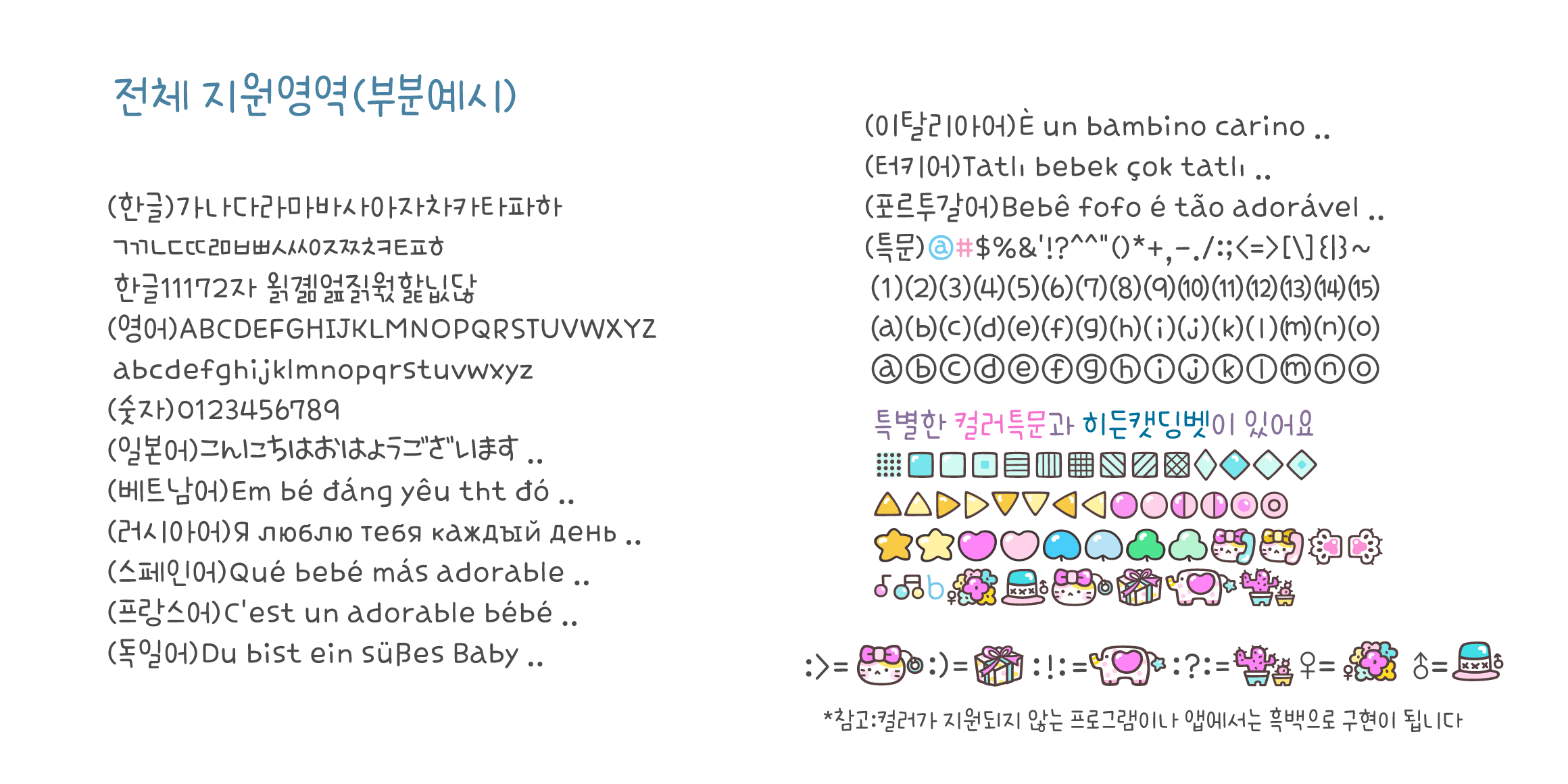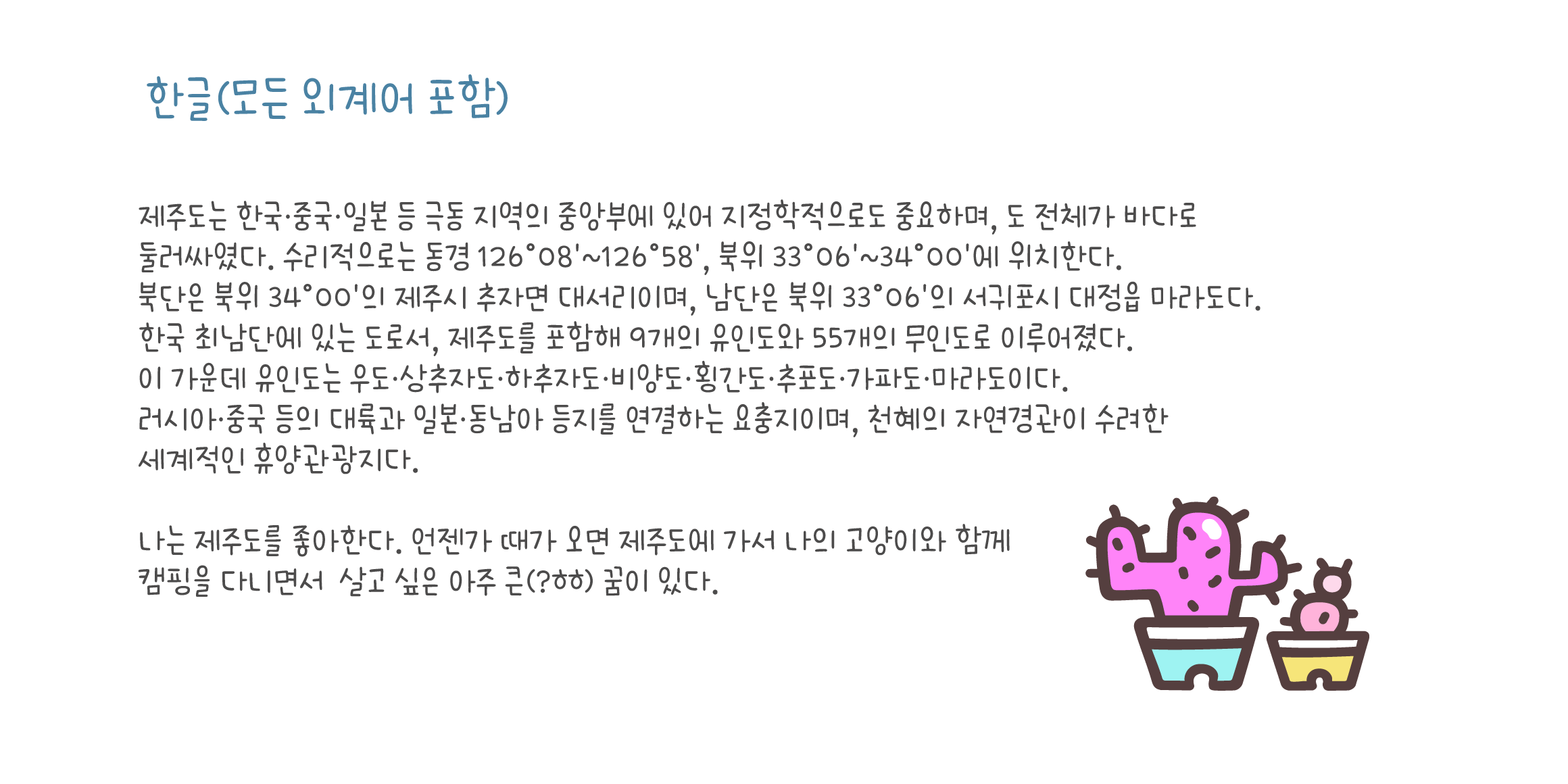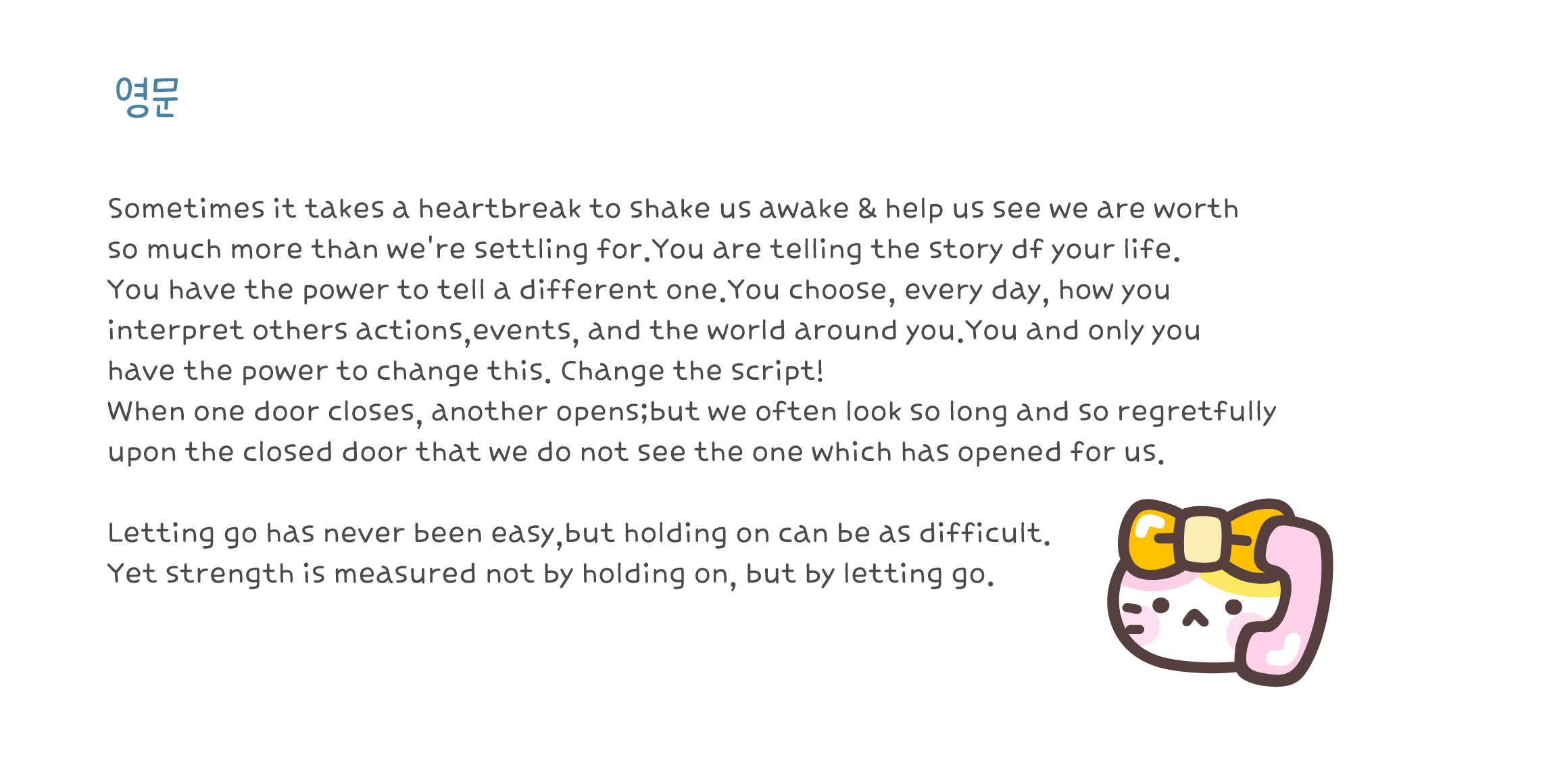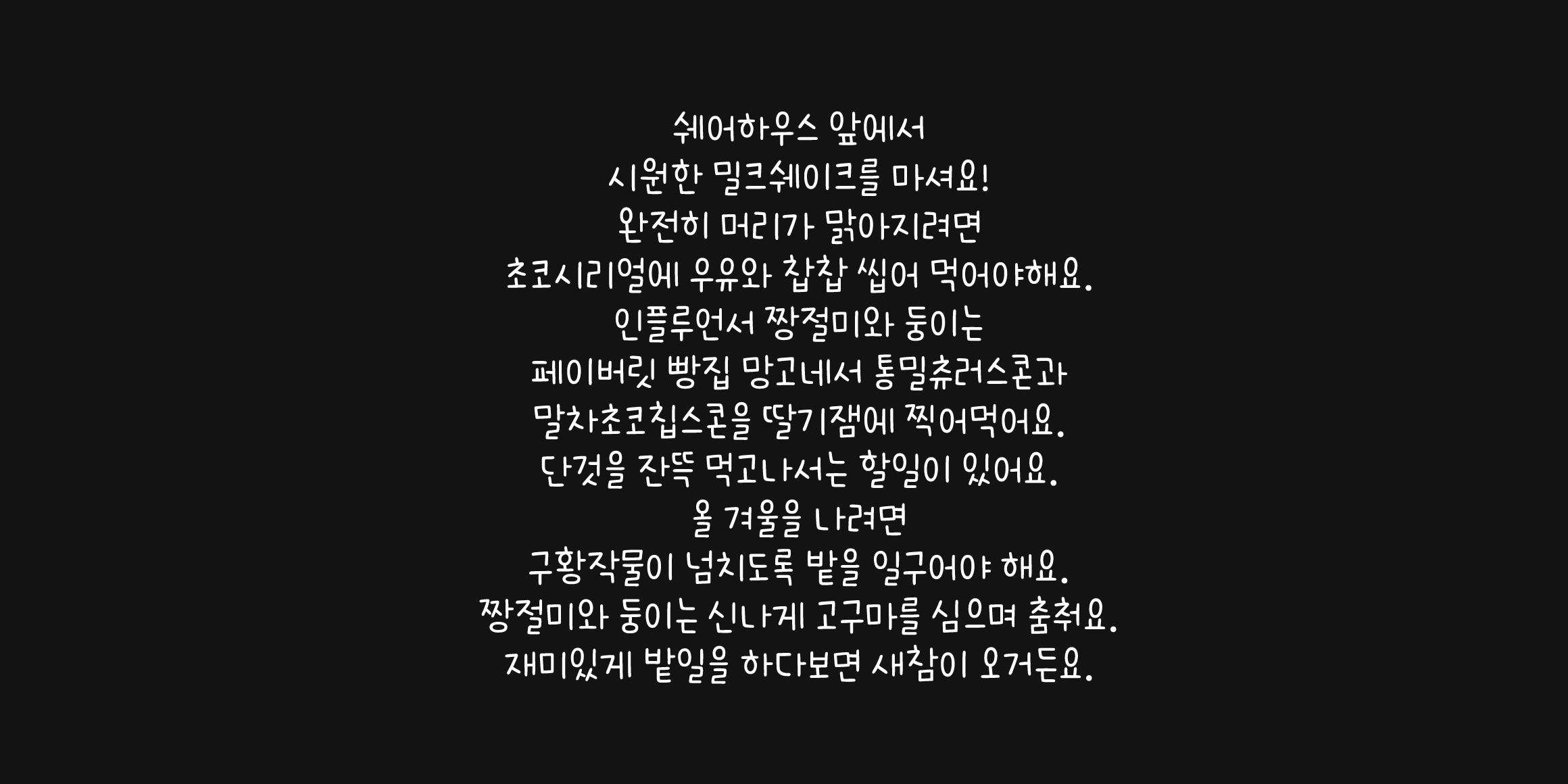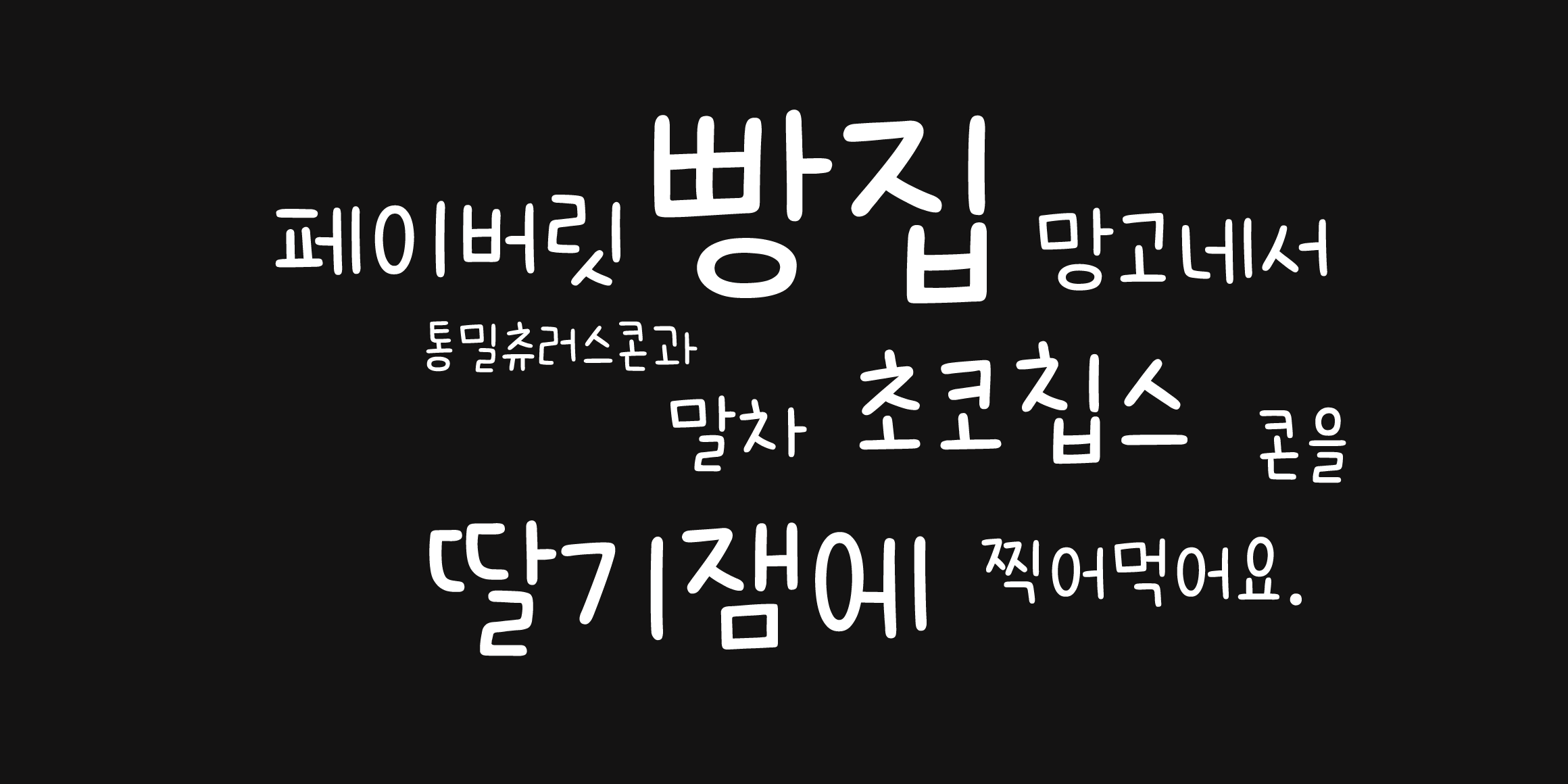
(캣폰트 시즌2 입니다)
비가 조끔씩 내리는 어느 퇴근길에 발견한
묘한 느낌의 선물가게에 있는
특이하고 아기자기한 소품 같은
독특함을 가진 귀여운 폰트입니다.
♥키보드 ; > ; ) : ! : : ? : 을 연달아 치면
매력적인 캣딩벳이 나타납니다.
♥영어 일어 베트남어를 포함한
독일 프랑스 러시아 이탈리아 포르투갈 스페인 터키 등
유럽의 다양한 국가들의 언어도 함께 지원하는 등
폭넓은 언어와 특수문자 지원을 합니다.
♥캣폰트의 디자인은 오랜 시간 연구한 결과물입니다.
*컬러가 지원되지 않는 단말기나 앱이 있을 수 있습니다.
*컬러가 들어간 글자들은 두껍게(Bold)처리를 해도 두께 변화가 없습니다.
♥catfont is your pet!
- Cat2묘한선물가게 / Cat2StrangeGiftShop